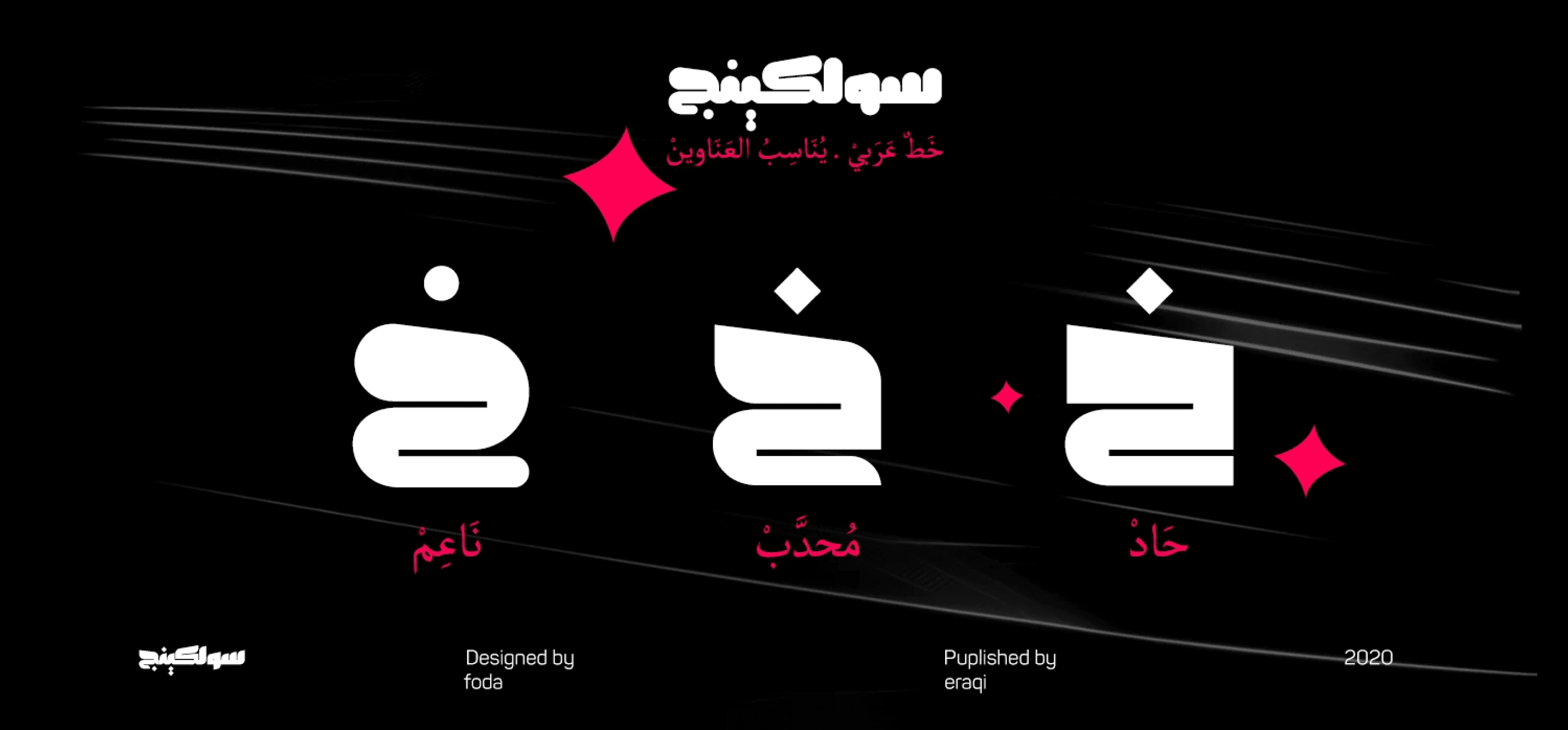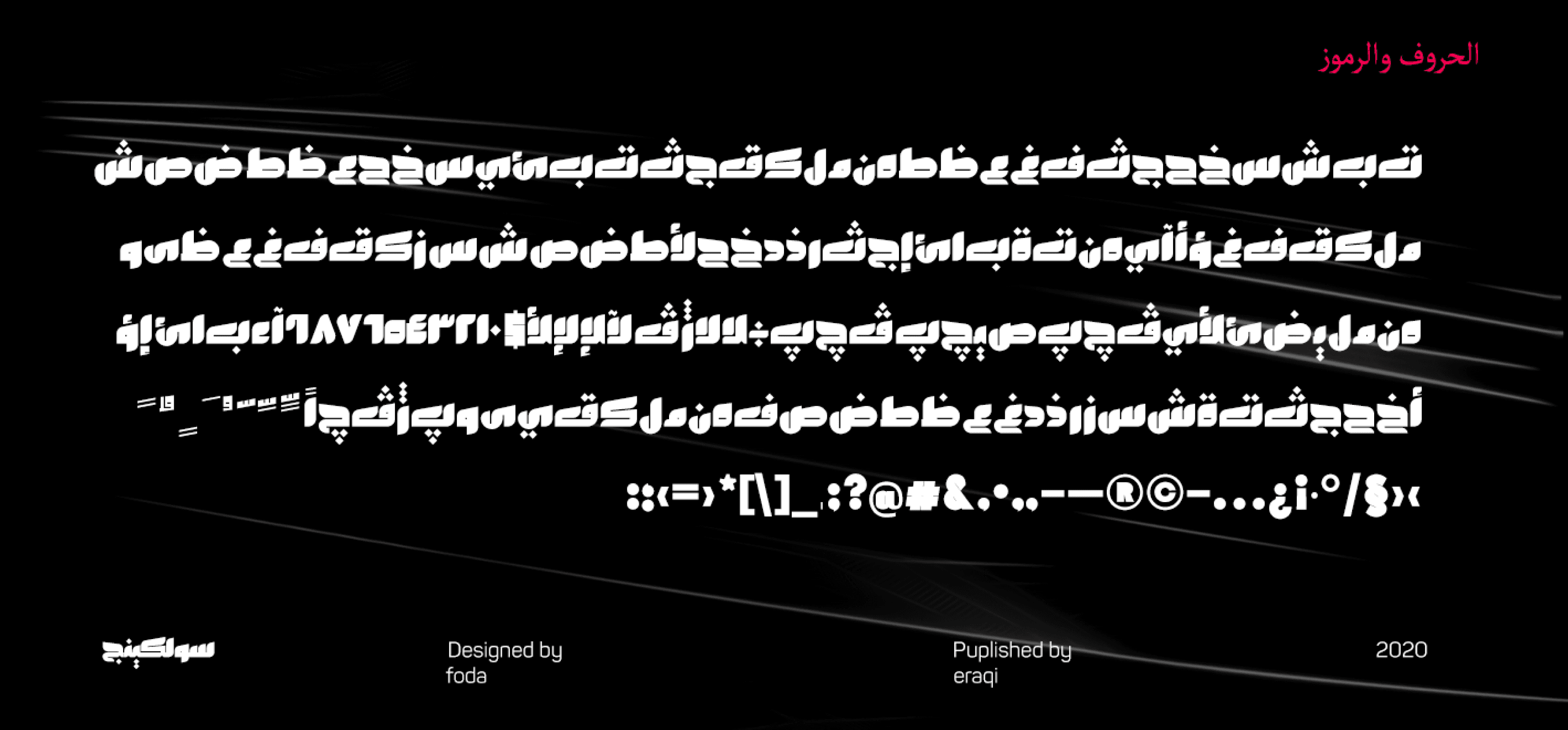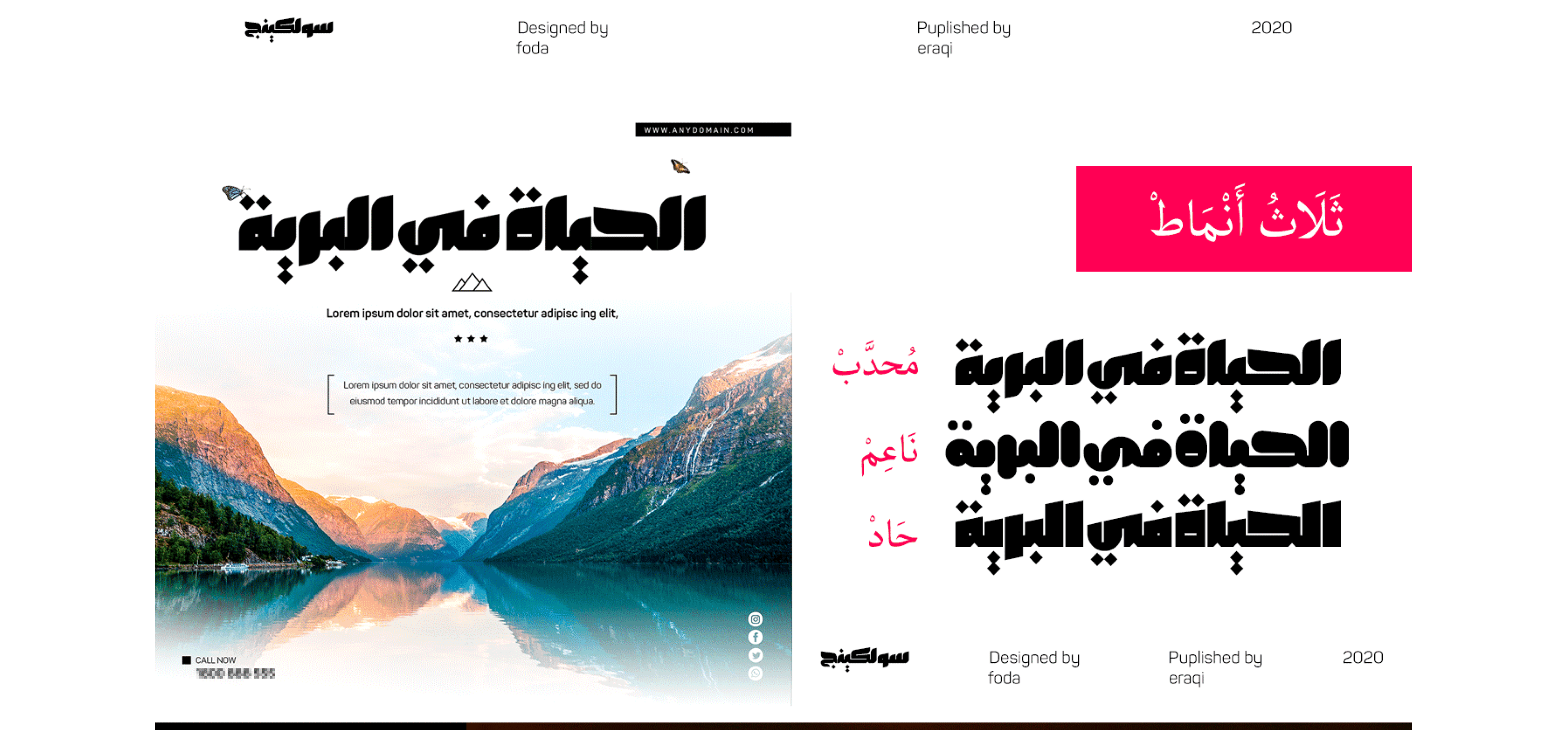
خط Solking هو خط عربي يتوفر بثلاثة أوزان: الحاد (Sharp)، والمنحني (Curved)، والمستدير (Rounded).
يركّز التصميم بشكل أساسي على دمج القواعد التقليدية والحديثة في صياغة وتطوير الخط الكوفي بأسلوب جديد ومبتكر.